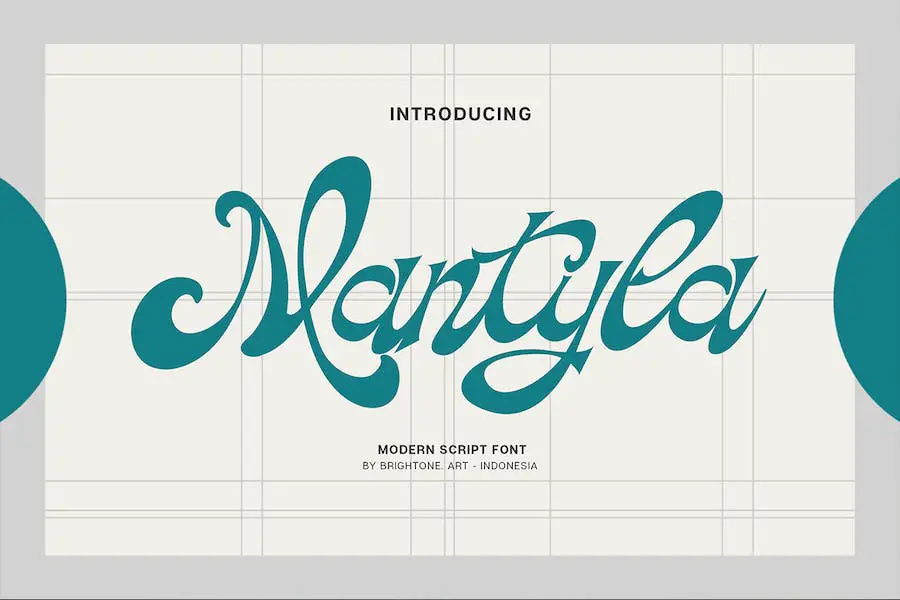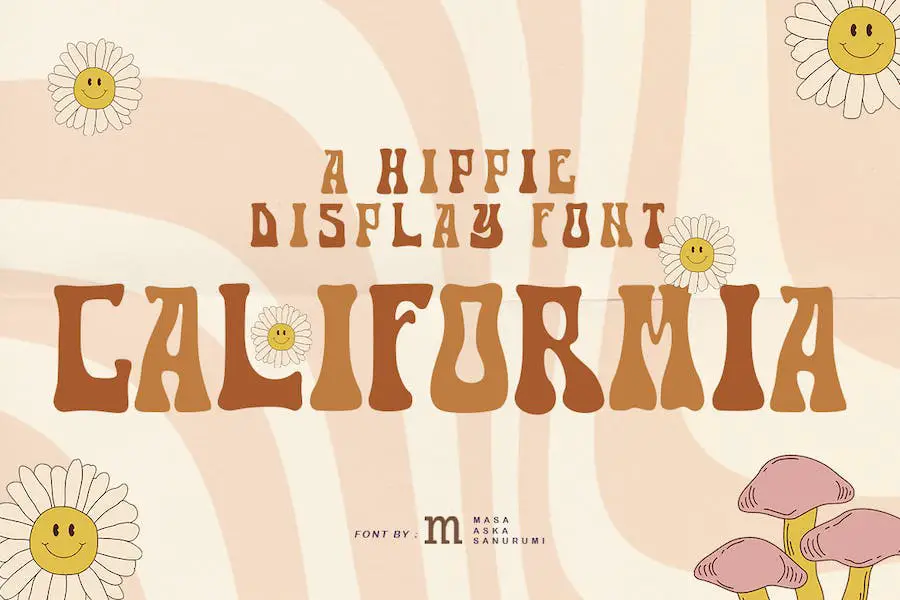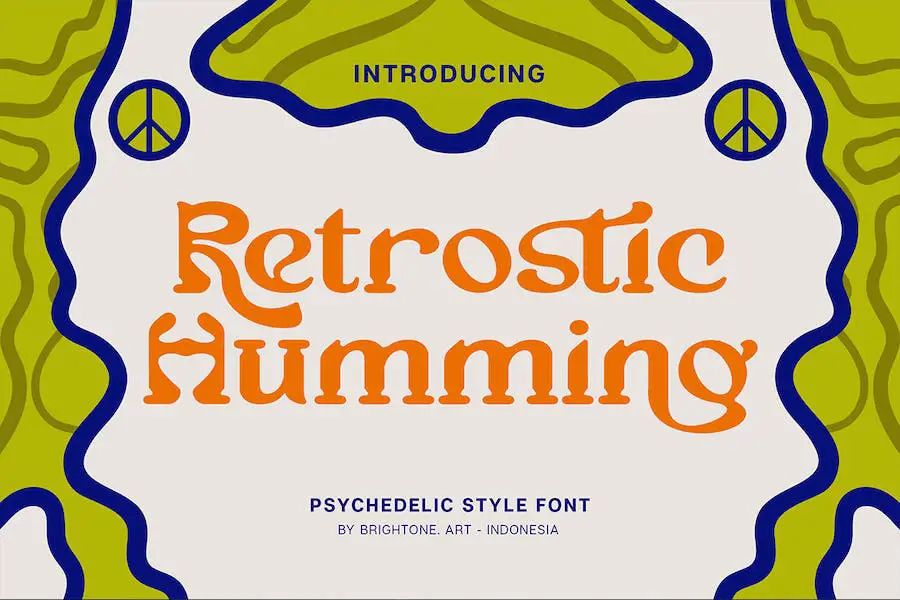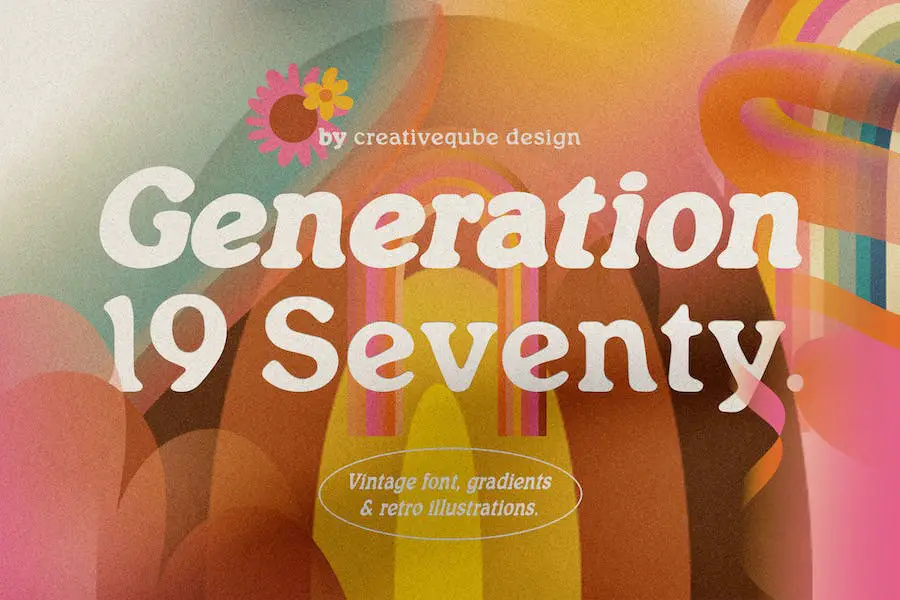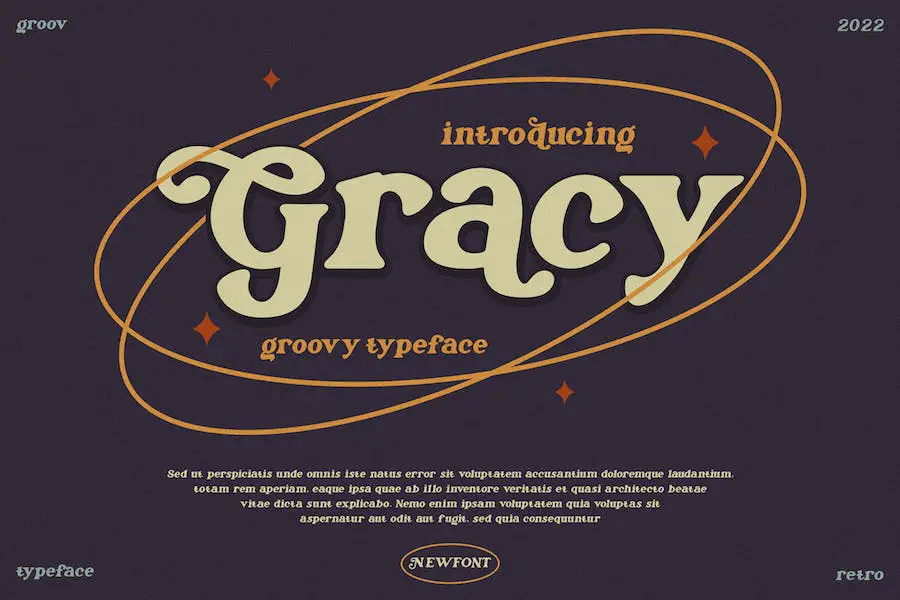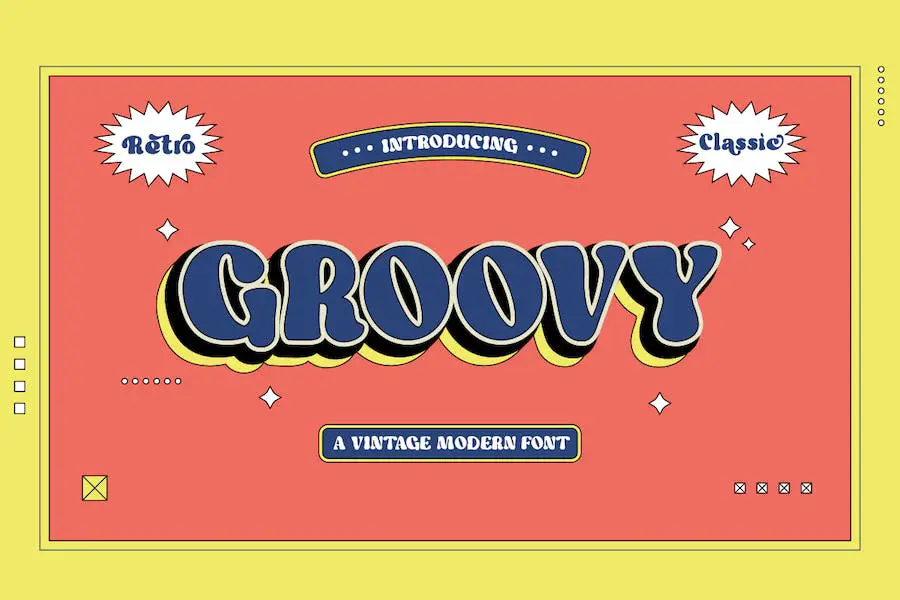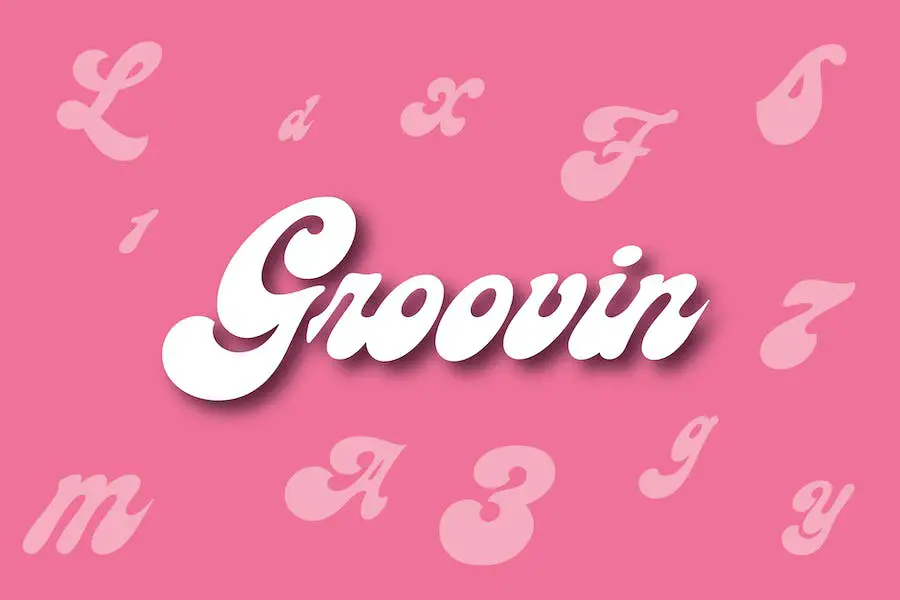
26 Font Hippie Terbaik 2023 (Gratis & Premium)
Diterbitkan: 2023-09-07Hai rekan-rekan desainer grafis! Apakah Anda bosan menggunakan font lama yang sama dalam desain Anda dan ingin menambahkan sentuhan asyik pada proyek Anda?
Nah, Anda datang ke tempat yang tepat! Dalam postingan blog ini, kita akan menjelajahi 26 font hippie terbaik yang akan menghadirkan kesan dinamis dan retro pada desain Anda. Namun sebelum kita mendalaminya, Anda mungkin bertanya-tanya, “Apakah saya benar-benar membutuhkan font hippie untuk proyek saya?” Baiklah, izinkan saya mengatasi kekhawatiran itu!
Sekarang mari kita bahas judul blog – 26 Font Hippie Terbaik. Pada artikel ini, kami akan menyajikan kepada Anda koleksi 26 font unik dan menarik yang dikuratori dengan cermat yang pasti akan menyempurnakan desain proyek Anda.
Font ini terinspirasi oleh era asyik dan berjiwa bebas di tahun 1960an dan 1970an, menghadirkan nuansa nostalgia dan artistik pada desain Anda. Selain itu, kami akan membagikan beberapa statistik dan fakta menarik tentang setiap font untuk membantu Anda membuat pilihan terbaik untuk proyek Anda.
Jadi, apa yang bisa Anda harapkan dari artikel ini? Nah, bersiaplah untuk memulai perjalanan tipografi saat kami membawa Anda melalui pilihan 26 font hippie yang menakjubkan.
Baik Anda sedang mengerjakan poster retro, logo bergaya vintage, atau bahkan situs web keren, font-font ini pasti akan membawa proyek Anda ke level berikutnya.
Jadi, tanpa basa-basi lagi, mari kita mulai dan jelajahi dunia font hippie bersama-sama!
Font Hippie Premium Terbaik
Ingin meningkatkan proyek desain grafis Anda dengan nuansa retro yang asyik? Lihat koleksi 26 Font Hippie Terbaik kami. Font premium ini akan membawa desain Anda kembali ke era kedamaian, cinta, dan tipografi yang dinamis.
Jadi mengapa menunggu? Selami dan temukan font yang sempurna untuk membawa proyek Anda ke tingkat yang benar-benar baru.
Unicorn Hippie
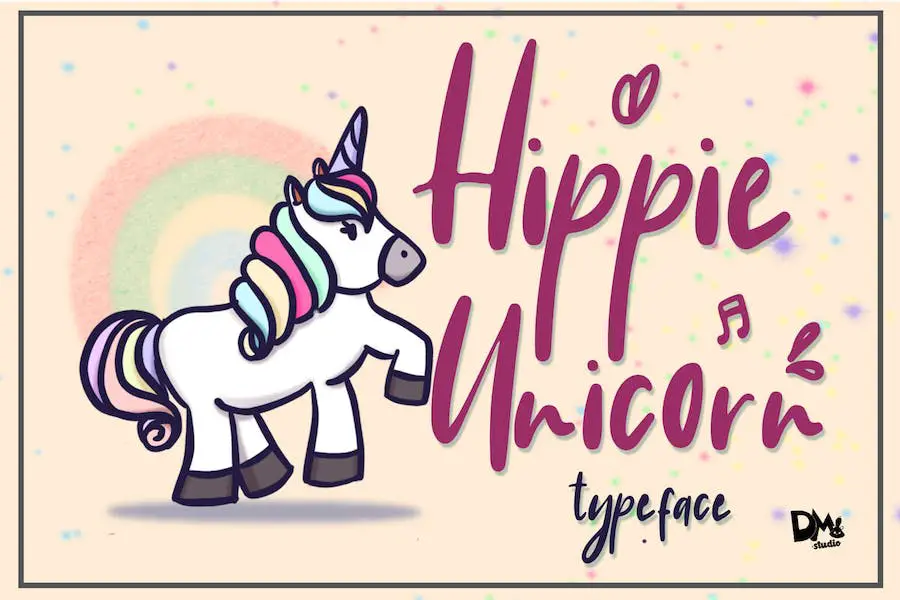
Hippie Unicorn adalah font tulisan tangan yang trendi dan apik yang dapat meningkatkan desain proyek apa pun. Baik Anda membuat kartu ucapan, pamflet, kartu nama, kutipan, atau materi branding, font ini adalah pilihan yang tepat.
Bahkan dilengkapi dengan garis bawah tambahan dan coretan unicorn yang digambar tangan, menambahkan sentuhan unik pada desain Anda.
Jenis huruf modern ini sangat serbaguna dan dapat digunakan untuk berbagai proyek kreatif. Nuansa tulisan tangannya yang asli menambah sentuhan pribadi dan unik pada karya Anda.
Dengan suasananya yang penuh gaya dan menyenangkan, Hippie Unicorn sangat populer untuk proyek yang melibatkan anak-anak atau bagi mereka yang ingin menanamkan rasa senang dan imajinasi ke dalam desain mereka.
Garis bawah tambahan memberikan opsi penyesuaian lebih lanjut, memungkinkan Anda menyempurnakan tata letak tipografi dan menciptakan penekanan yang menarik. Dan siapa yang bisa menolak coretan unicorn yang digambar tangan dan menggemaskan?
Mereka dengan mudah menghadirkan sentuhan ajaib pada desain apa pun, menjadikannya sempurna untuk proyek anak-anak, pembuatan scrapbook, atau apa pun yang membutuhkan sedikit pesona.
Hippie Kosmik
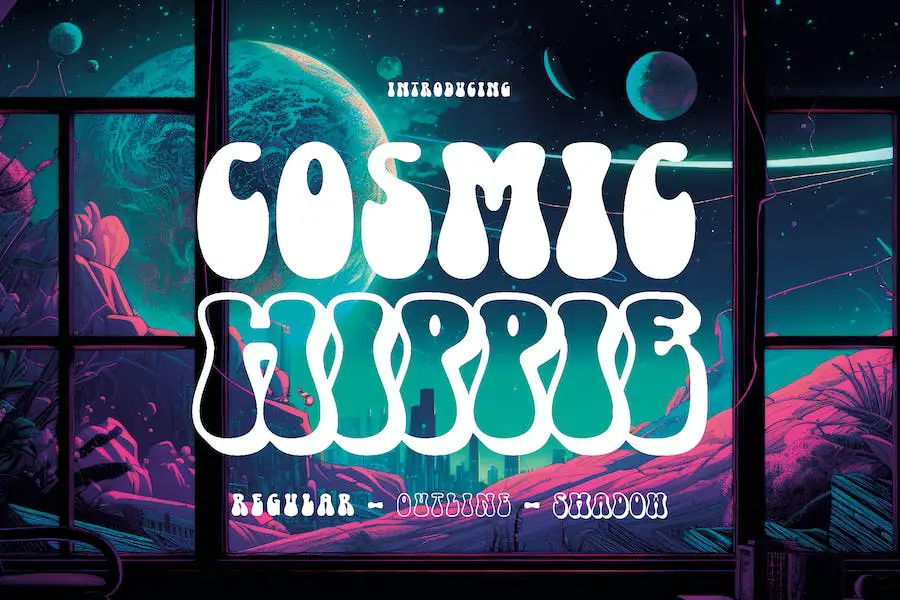
Cosmic Hippie adalah font asyik yang membawa Anda kembali ke tahun 1970-an yang penuh warna dan semarak. Ini mencerminkan semangat dekade ikonik tersebut, menjadikannya sempurna untuk desain dan proyek retro yang bertujuan membangkitkan nuansa nostalgia.
Dengan getarannya yang hidup dan berjiwa bebas, font ini menambahkan sentuhan individualitas dan keaslian pada desain apa pun.
Atribut Cosmic Hippie sungguh asyik. Ini menampilkan bentuk huruf yang unik dan menyenangkan yang mengingatkan pada tipografi yang digambar tangan pada tahun 70an. Setiap karakter memiliki nuansa aneh dan organik, menghadirkan kesan kepribadian dan karakter pada desain Anda.
Font ini juga menyertakan berbagai karakter dan pengikat alternatif, memungkinkan Anda bereksperimen dan membuat huruf khusus yang menonjol.
Salah satu hal terbaik tentang Cosmic Hippie adalah keserbagunaannya. Ini dapat digunakan dalam berbagai proyek desain, mulai dari poster dan sampul album hingga logo dan grafik media sosial.
Baik Anda sedang mengerjakan proyek branding yang terinspirasi gaya vintage atau ingin menambahkan sentuhan retro ke situs web, font ini siap membantu Anda.
Hippie antik
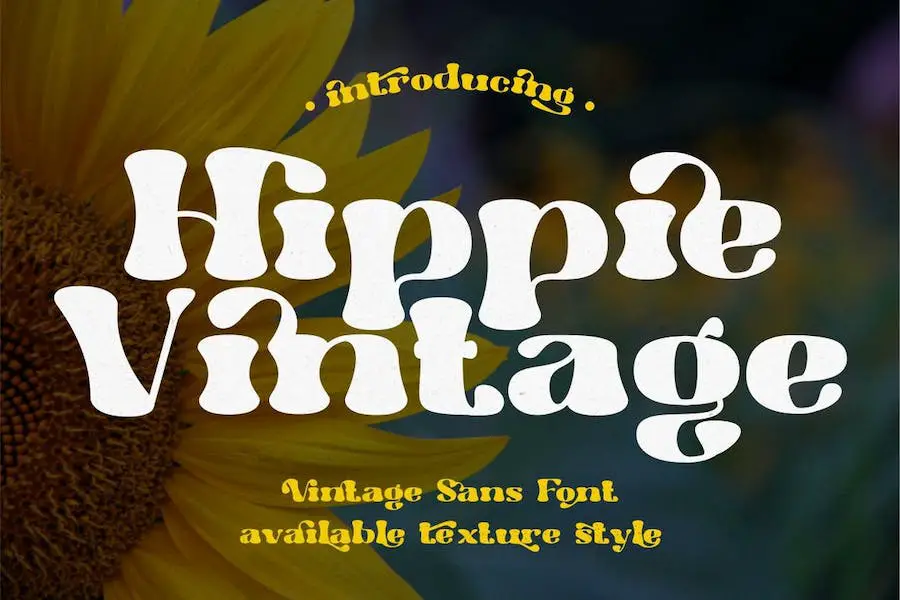
Hippie Vintage adalah font sans serbaguna yang menangkap esensi berani dan asyik dari desain klasik tahun 60an. Dengan nuansa vintage, font ini menambahkan sentuhan bersih dan unik pada proyek apa pun.
Baik Anda sedang mengerjakan poster bertema retro atau membuat logo nostalgia, Hippie Vintage adalah pilihan sempurna untuk menghidupkan suasana vintage.
Font ini menonjol dengan karakternya yang berani dan menarik, membuat pernyataan dalam desain apa pun. Bentuknya yang bersih dan bulat memberikan daya tarik abadi yang melengkapi tema vintage dengan sempurna.